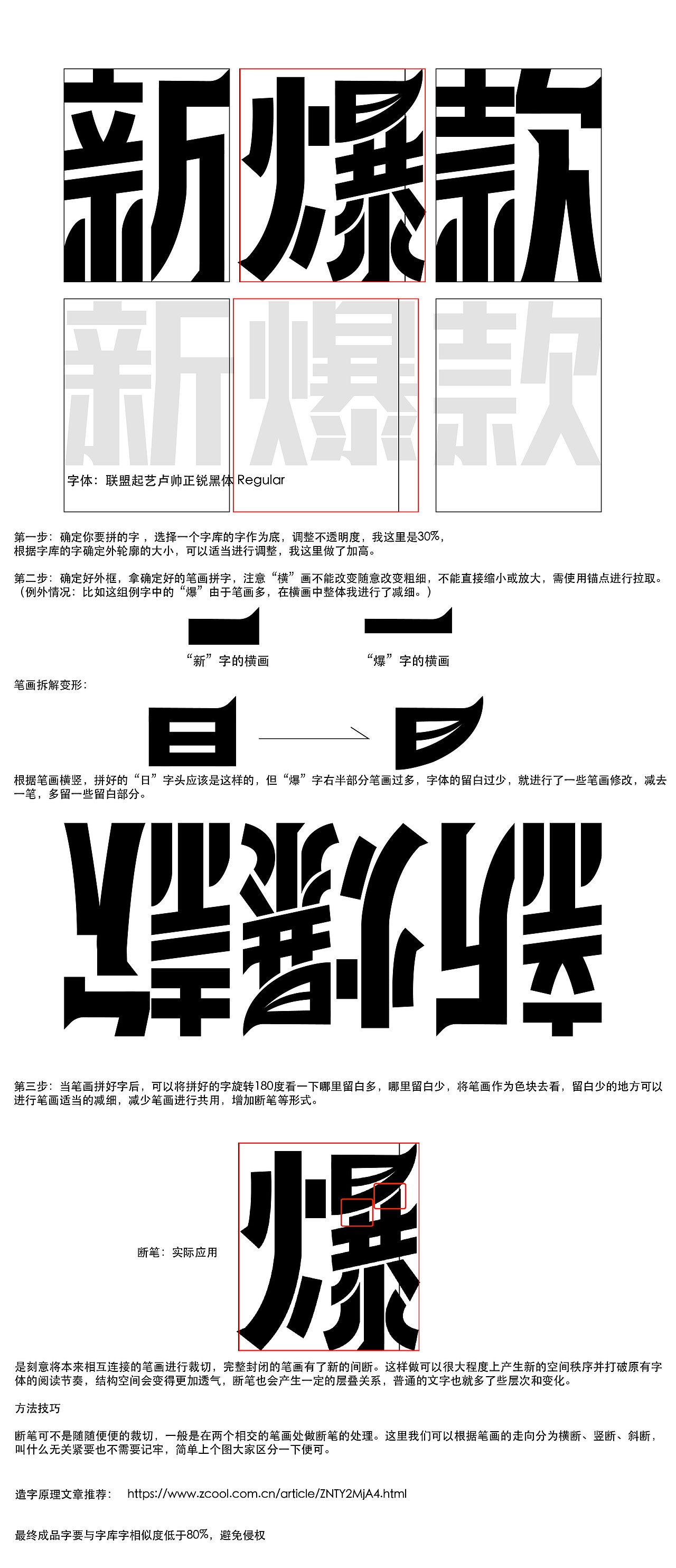
近期字体学习总结
我很喜欢的一个字体设计案例
字体设计要注意的点
1.字体的疏密布白(留白/负空间)
2.字体的笔画粗细
(横粗竖细、主粗副细、外粗内细、疏粗密细、交叉减细)
3.字的重心
字的重心会影响字的气质,重心高的字会给人清瘦雅的感觉,重心低的字会给人稳厚拙的感觉
4.字的中宫
5.字面与字身
造字开始